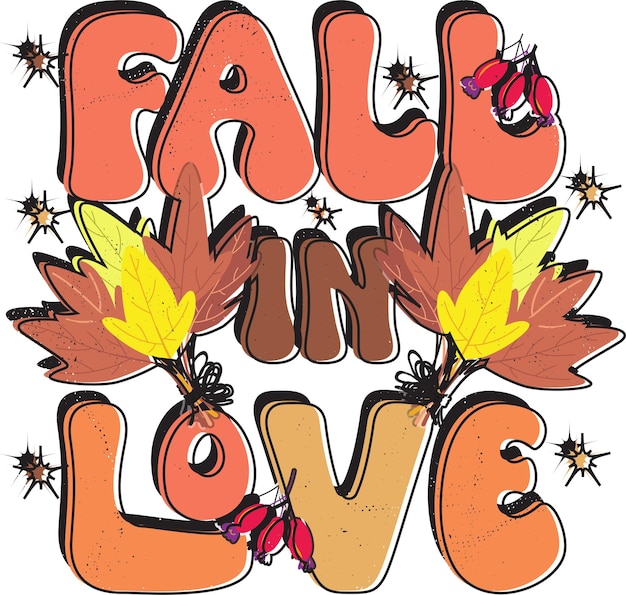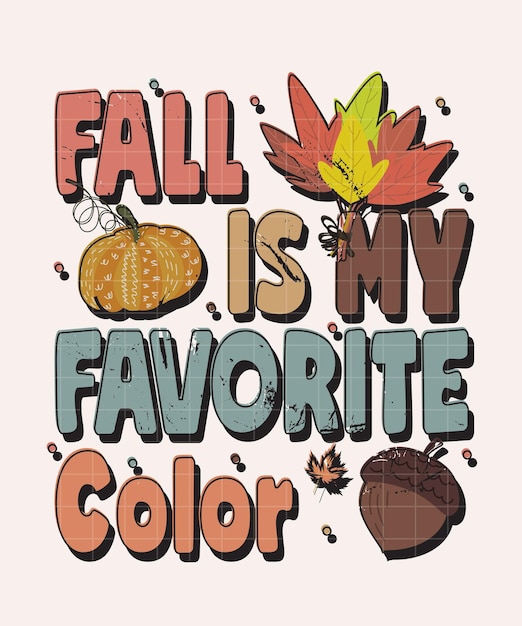
groovy jesień typografia napis projekt, projekt koszulki z napisem Święto Dziękczynienia, fajna koszulka
Groovy jesień typografia napis projekt, projekt koszulki z napisem Święto Dziękczynienia, fajna koszulka